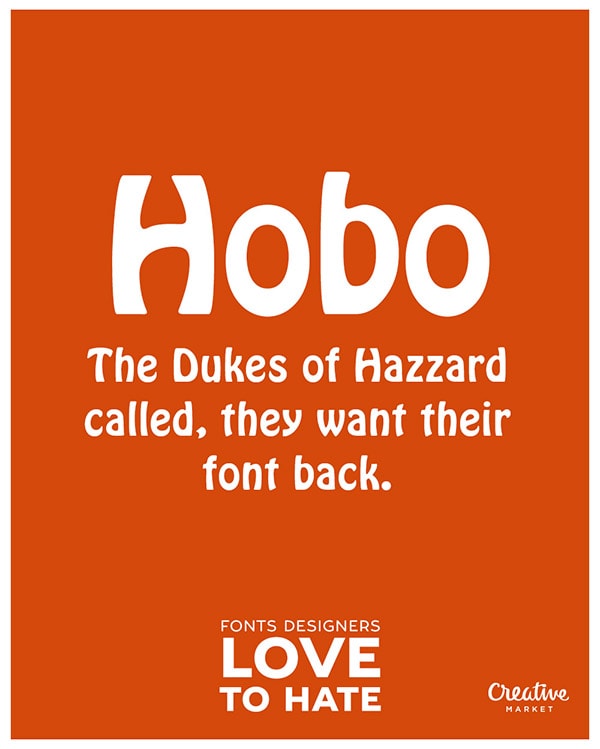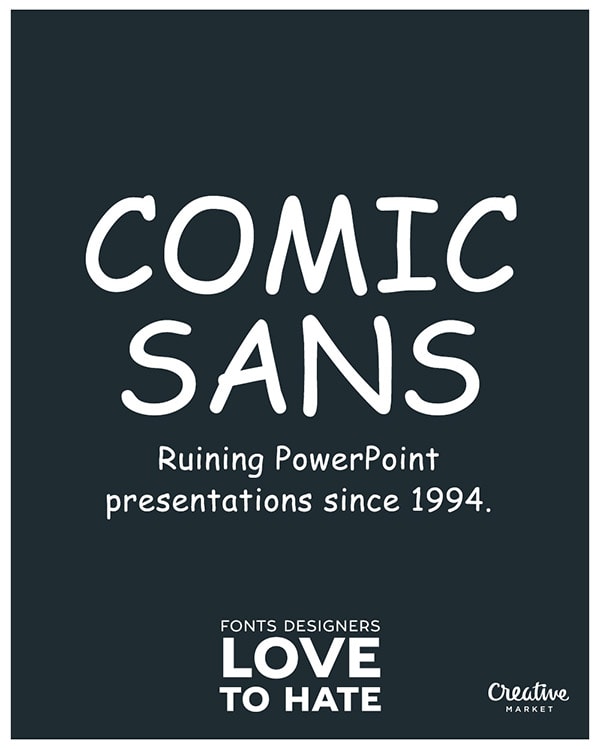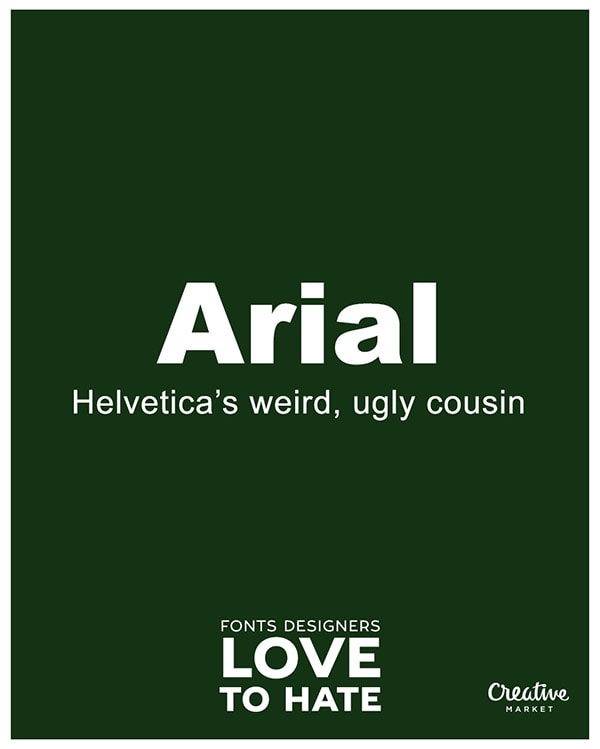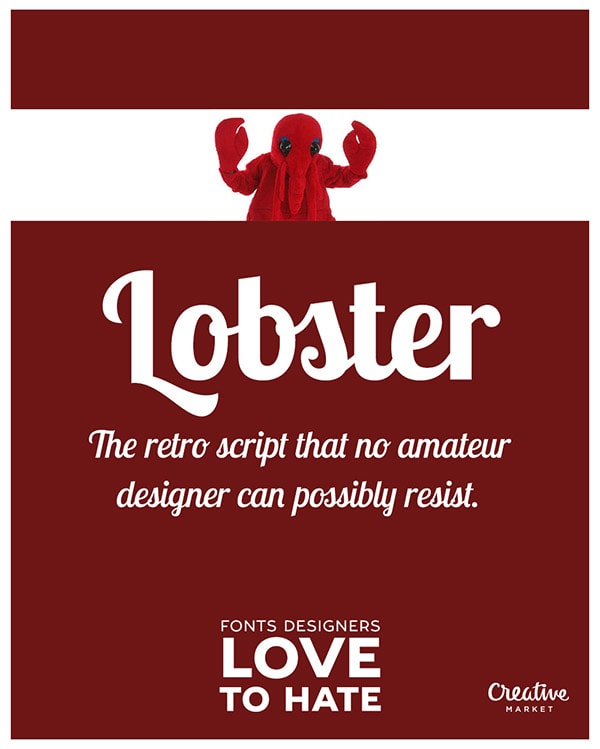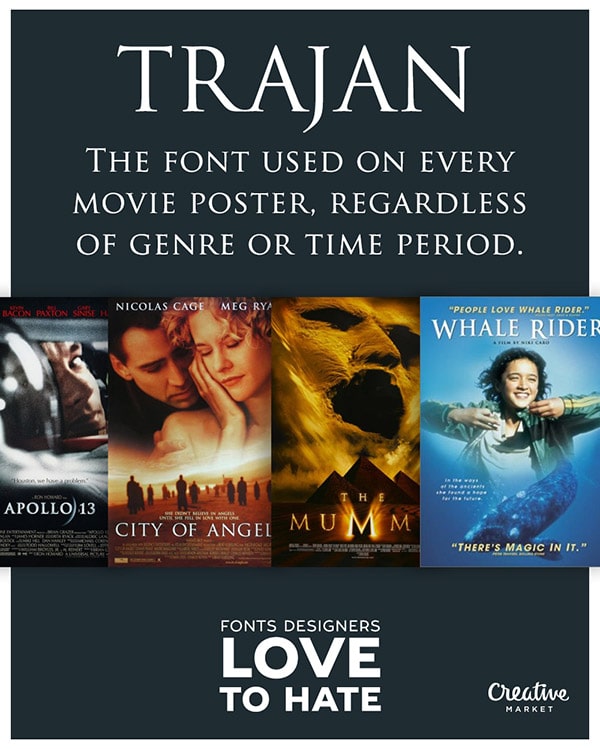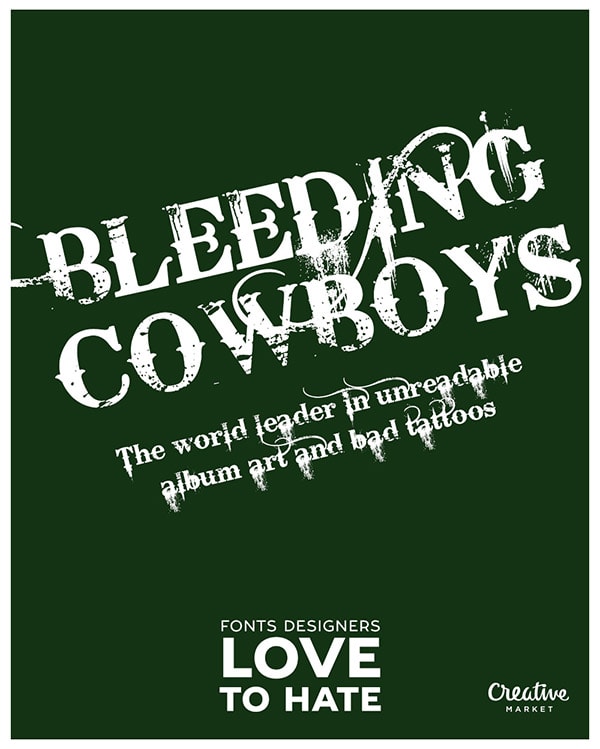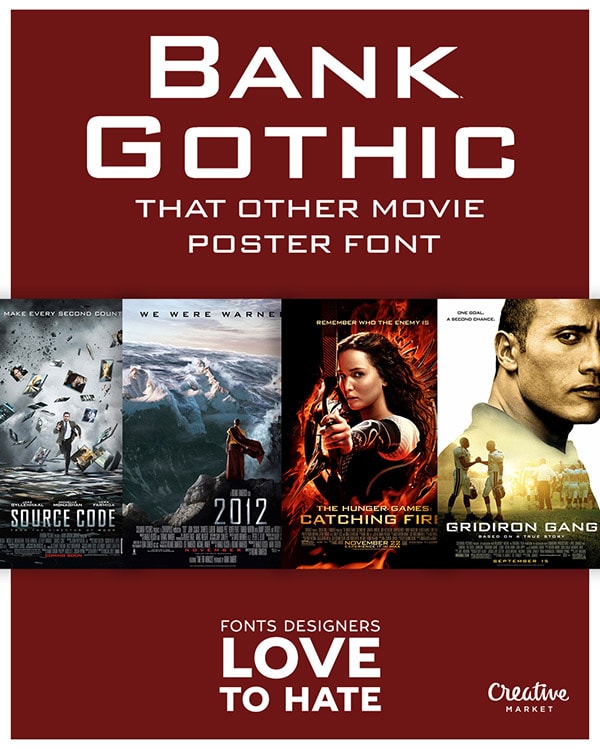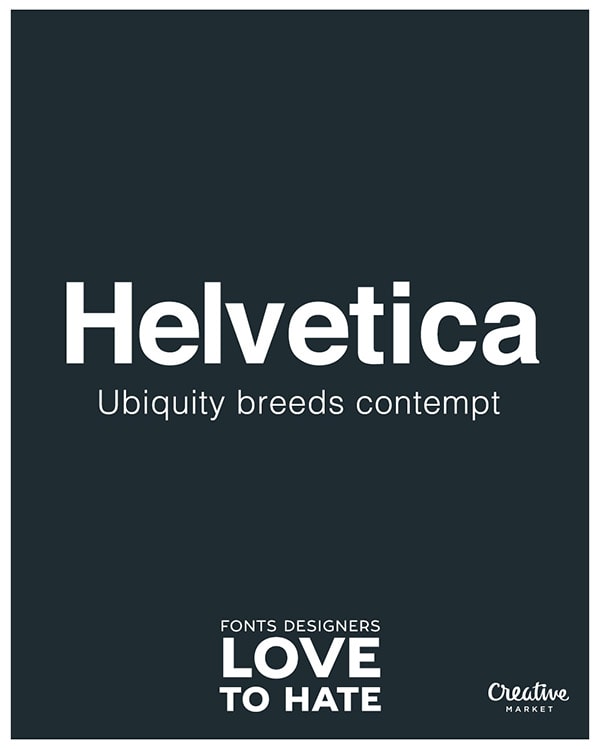
Il y a des polices d’écriture qui souffrent tellement d’avoir été utilisées à outrance qu’elles en sont devenues détestables. Beaucoup penseront à la Comic Sans MS, mais elle n’est pas la seule. En voici quelques-unes décrites avec humour.
Nous avons tous des typographies qui nous font horreur. Les raisons peuvent être très variées : trop utilisée, mauvaise conception, perte de son caractère (voyez le jeu de mots pourri) de par son usage abusif et j’en passe. Je garde toutefois un faible pour les versions alternatives de deux d’entre-elles : la Lobster Two (alternative à la désormais trop connue Lobster) et la Helvetica Neue (alternative à la Helvetica, elle est extrêmement pratique pour un usage institutionnel ou pour de l’affiche devant être vue de loin).
Réalisés par Creative Market, voici onze exemples de polices qui ont tendance à susciter le rejet chez la plupart des designers. Gageons qu’il y en a au moins quelques unes contre lesquelles vous allez pester.
Cet air de faux égyptien est tellement tendance. Ou pas.
Car aucun polycopié de votre scolarité ne se lisait mieux qu’avec du Times New Roman.
Est-il réellement nécessaire d’en parler ?
La typo du générique de « Shérif, fais-moi peur ». Ouais ouais.
L’ubiquité engendre le mépris.
Cette autre police d’affiche de film.
Leader mondial dans l’illisibilité des pochettes de l’album et des books de tatouages.
La police utilisée sur toutes les affiches de film, peu importe le genre, ou de la période.
Le typo rétro à laquelle aucun graphiste amateur ne peut résister.
Le cousin laid et bizarre de la Helvetica.
La police que Zorro aurait voulu utiliser pour ses invitations de mariage.